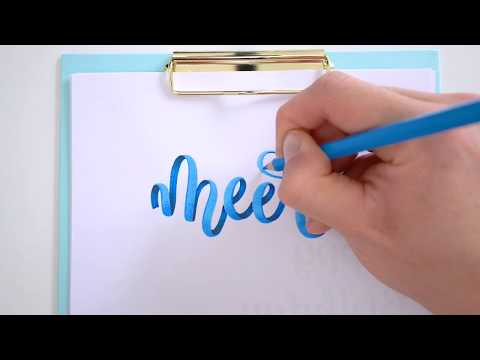
Bunte Ribbon Letterings wirken besonders dynamisch und haptisch. Die Erstellung von realistische Ribbons (zu Deutsch: Bänder / Schlaufen) macht super viel Spaß, ist aber nicht ganz einfach.
Deshalb findest du hier eine detaillierte Ribbon Lettering Anleitung! Mit den richtigen Tipps und Techniken werden auch dir fantastische Ribbons gelingen.
Der Blick in die Wirklichkeit
Bei all der Kreativität, den verschiedenen Strichen und Techniken darfst du eines nicht vergessen:
Wenn du einen realistischen Effekt nutzen möchtest, dann schau auch mal in die Realität!
In diesem Fall heißt das, dass wir einen Blick auf ein echtes Geschenkband werfen. Dieses Vorgehen empfehle ich genau so bei der Zeichnung von Bannern und Fähnchen.
So können wir ganz genau sehen, was die Optik eines Ribbons ausmacht.
- Wie sehen die Übergänge aus?
- Wo sind dunkle und helle Bereiche?
- Wie laufen die Kanten?
Und damit du jetzt nicht sofort ein Band suchen musst, habe ich natürlich ein passendes Foto für dich. Dort habe ich eine ganz simple Linienführung nachgeahmt.
Wenn du dir das Foto im Detail anschaust, siehst du folgende wichtige Faktoren:
- Das Band ist (logischerweise) immer gleich breit. Minimale Unterschiede ergeben sich durch die Entfernung zur Kamera bzw. zum Auge.
- Der hintere Bereich des Bands ist dunkler, als der vordere Bereich.
- Die Kanten heben sich zusätzlich ab.
- Auf den vorderen Schlaufen sind weitere Lichtreflexionen zu sehen.
Diese Faktoren variieren, je nach Beleuchtungsart- und Winkel. Für gewöhnlich haben wir aber eine Beleuchtung von oben, sodass die typische Optik sich meist sehr ähnelt.
Und genau diese Optik werden wir jetzt mit einem Brushlettering und der passenden Technik nachahmen!
Techniken im Überblick
Es gibt viele verschiedene Möglichkeiten, ein Ribbon zu kreieren. Ob komplett mit einem Bleistift, mit verschiedenen Brushpens oder einer Keilspitze.
Sobald du das Prinzip verstanden hast, kannst du die verschiedenen Herangehensweisen nutzen oder nach Belieben kombinieren.
Folgendes Foto gibt dir einen Überblick über die vielen Möglichkeiten.
- Erstellung des Ribbons mit Hilfe zweier, versetzter Linien. Zum Beispiel mit einem Bleistift oder Fineliner.
- Die Nutzung von zwei Brushpens gleichen Farbtons aber verschiedener Helligkeiten. Die hintere Linie wird hier nachträglich verbreitert.
- Der Einsatz einer Keil- oder Flachspitze (wie bei einem Textmarker). Hier ergibt sich das Band fast automatisch, wenn die Spitze stets im gleichen Winkel geführt wird.
- Ribbon Lettering mit einer Konturlinie. Der starke Kontrast der Linie sorgt dafür, dass die einzelnen Teilstücke deutlich erkennbar sind.
- Ein abstrahiertes Ribbon, bei dem die Linien nur mit einem Brushpen gezogen wurden. Dabei werden lediglich die hinteren Linien (meist Aufstriche) verdunkelt.
- Zur Schattierung eignet sich auch ein Buntstift. Damit hast du sehr viel Kontrolle über die Schattierung und es kann nichts verlaufen.
In dieser Anleitung zeige ich dir, wie du mit Herangehensweise Nummer 4 ein schönes Ribbon Lettering zaubern kannst.
Das einfachste Ribbon Lettering
Beim Ribbon Lettering gibt es im Prinzip zwei Herausforderungen:
- Die Basis Form richtig erstellen
- Die fertige Form so bemalen, dass der Ribbon-Effekt entstehen kann
Daher starten wir jetzt mit einer ganz basischen Form des Ribbon Letterings mit Hilfe von Brushpens und einer dunklen Kontur.
Die Grundform
Als erstes schreibst du das gewünschte Wort mit deinem Brushpen. Folge dem typischen Rhythmus von Ab- und Aufstrichen.
Die Abstriche sind später der vordere Teil des Ribbons, die Aufstriche bilden das hinten liegende Band.
Achte ggf. auf eine erhöhte Spationierung (die Abstände zwischen den einzelnen Buchstaben), damit du später ausreichend Platz hast.
Die Aufstriche verbreitern
Im zweiten Schritt verbreiterst du die Aufstriche. Sie sollten genau so breit sein, wie die Abstriche.
Bei diesem Prozess solltest du bereits im Hinterkopf haben, wie sich deine Verbreiterungen später auf dein Ribbon auswirken. Mit der Zeit wirst du dafür ein Gefühl entwickeln!
Es ist auch möglich, die Linien immer mit gleichem Druck (also ohne unterschiedliche Auf- und Abstriche) zu ziehen, um die nachträgliche Verbreiterung zu vermeiden. Allerdings tut das dem Brushpen absolut nicht gut und er wird schnell ausfransen. Nimm dazu auf jeden Fall nur einen ausrangierten Stift!
Die Konturen definieren
Die Konturen helfen dabei, die einzelnen Bereiche klar abzugrenzen. Das ist zwar nicht komplett realistisch, hilft aber enorm bei der Definition der kritischen Bereiche. Das sind die Übergänge von hinten nach vorne und die Überlappungen.
Schau dir das echte Band an. Dort habe ich die wichtigsten Konturen nachgezogen. Natürlich erhalten auch die anderen Kanten eine Kontur.
Dieses Prinzip überträgst du nun auf deinen Schriftzug. Gehe damit möglichst Schritt für Schritt vor und überlege dir vor jeder Linie genau, wie sie verlaufen müsste. Bei diesem Schritt passieren schnell Flüchtigkeitsfehler.
An diesem Punkt ist bereits ein leichter Ribbon-Effekt wahrnehmbar!
Die Rückseite ausmalen
Indem du nun die hinteren Bereiche des Bands mit einem dunkleren Brushpen des gleichen Farbtons ausfüllst, wird der Ribbon-Effekt intensiviert.
Gibt dein Brushpen sehr viel Farbe ab, reicht es manchmal auch, die hinteren Bereiche mehrfach mit der gleichen Farbe zu übermalen.
Achte hierbei wieder besonders auf die Übergänge. Schau dazu auch nochmal auf des echte Satinband und sieh dir an, wie die Rundung im Übergang verläuft.
Warte vor diesem Schritt, bis die Farbe wirklich getrocknet ist und nicht mehr verlaufen kann. Sonst erhältst du unsaubere Kanten.
Die Kombination aus hellem Vordergrund und dunklem Hintergrund stellt eine der simpelsten Möglichkeiten dar, ein Ribbon Lettering zu erstellen.
Du kannst den Hintergrund theoretisch auch schwarz füllen, um dein Ribbon zu visualisieren. Das wäre ein simple (aber trotzdem schicke) Variante und sähe dann beispielsweise so aus:
Allerdings hast du dann keine Möglichkeit mehr, im Hintergrund mit Verläufen und weiteren Schatten zu arbeiten. Deshalb nutzen wir in unserem Beispiel keine schwarze Rückseite.
Mit weiteren Techniken und Details kannst du den Effekt zusätzlich verstärken.
Details ergänzen
Jetzt ist es an der Zeit, unser Ribbon Lettering durch weitere Details zu verschönern. Erinnern wir uns dazu erneut an ein echtes Geschenkband und die verschiedenen Helligkeiten.
Als erstes ergänzen wir die Schatten im Bereich der Schlaufen. Dieser Bereich ist meist dunkler, da dort weniger Licht hinkommt.
Dabei ist es hilfreich, wenn du bereits mit Verläufen vertraut bist.
In Kurzform: Gib ein kleines bisschen Farbe mit dem dunkleren Stift in dem entsprechenden Bereich ab. Setze sofort danach den helleren Stift ein, um die dunkle Farbe zu verblenden.
Auch im Vordergrund verdunkeln wir den unteren Bereich, damit der oberere Bereich etwas heller ist.
Der 3D Effekt ist damit bereits deutlich verstärkt.
Im nächsten Schritt verstärken wir die Konturen unseres Geschenkbandes. Eine Seite wird hell bzw. weiß. Dadurch wird auch der wichtige Bereich des Übergangs noch deutlicher sichtbar. Hierzu nutze ich gern einen weißen Gel-Roller.
An diesem Punkt finde ich das Ribbon ausreichend optimiert und wirklich ansprechend! Optional kannst du nun noch zusätzliche Highlights (Lichter bzw. Lichtreflexe) hinzufügen.
Dies wäre in der Realität vor allem vom verwendeten Material abhängig. Ein typisches Satinband hat meist keine harten Lichtreflexe. Allerdings haben wir natürlich immer die Möglichkeit hier künstlerisch frei zu agieren.
Hauptsache dir ist bewusst, welchen Effekt du mit welcher Herangehensweise erzeugst.
Zu guter Letzt habe ich den Schriftzug natürlich noch passend verziert.
Ribbon Lettering im Zeitraffer
Zur Verdeutlichung der Technik habe ich auch noch einmal einen Zeitraffer für dich erstellt. Dort nutze ich für die zusätzlichen Schatten allerdings einen Buntstift.
Techniken kombinieren
Ein Ribbon Lettering sieht bereits in der einfachsten Variante wirklich toll aus. In Kombination mit anderen Lettering Techniken kannst du einen Schriftzug noch aufregender und dynamischer gestalten.
Als guter Partner für das Ribbon Lettering eignet sich zum Beispiel das Bounce Lettering. Die tanzenden Buchstaben sorgen für ein geniales Erscheinungsbild.
Auch Farbverläufe lassen sich in Kombination mit deinen Ribbons super einsetzen. Teilweise sind sie sogar nötig, um die verschiedenen Helligkeiten richtig einsetzen zu können.
Möchtest du richtig tief in das Ribbon Lettering einsteigen und unglaubliche Effekte erzielen, empfehle ich dir die Techniken aus Caros Ribbon Lettering Guide. Die Tricks bringen deine Ribbons noch einmal auf ein völlig neues Level!
Am Ende gilt aber immer: Lass Leidenschaft am besten freien Lauf und kombiniere nach Lust und Laune!